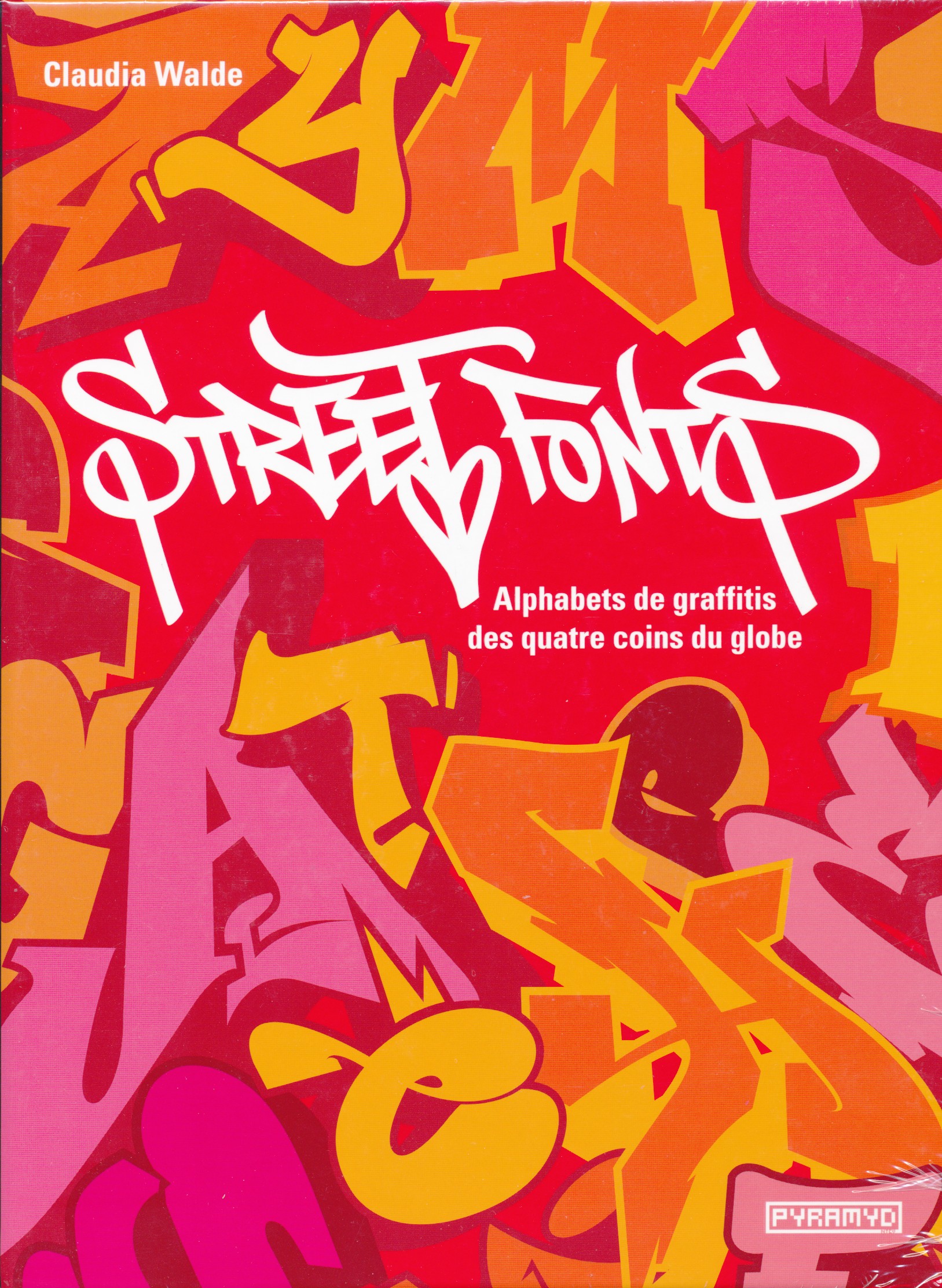
Cet ouvrage présente 154 alphabets réalisés par des graffeurs talentueux comptant parmi les plus créatifs de la planète. Ils nous livrent leur interprétation personnelle de l'alphabet latin, dans une variété de styles allant des lettres traditionnelles aux caractères les plus modernes.
Une double page est consacrée à chaque artiste : elle présente l'alphabet créé pour le livre ainsi que des oeuvres en situation et un témoignage sur le rapport de chacun à son art et au travail de lettrage.
Ce florilège de créations inspirera tous les amoureux des lettres et du graffiti !